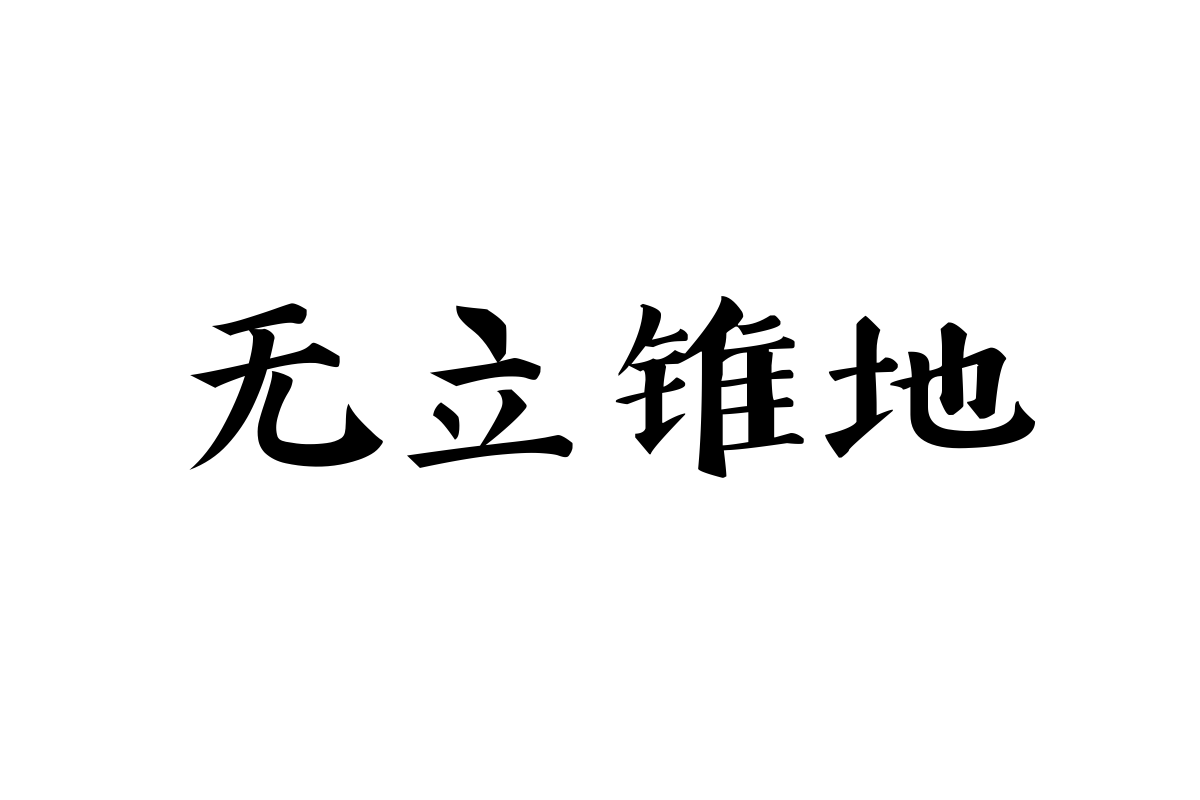
汉仪新蒂唐朝体是一套专为中文排版设计的字体,由汉仪字库公司推出。这套字体具有独特的风格和特点,旨在为设计师提供一种新颖、独特的字体选择。以下是对汉仪新蒂唐朝体的一些介绍:
1. 设计风格:汉仪新蒂唐朝体采用了唐朝时期的书法风格,笔画流畅、自然,具有很强的艺术感。这种设计风格使得字体看起来既有古典韵味,又不失现代感。
2. 字形结构:该字体的字形结构较为复杂,笔画较多,但整体布局紧凑,呈现出一种平衡和谐的感觉。这使得字体在视觉上具有较高的辨识度和美感。
3. 应用场景:汉仪新蒂唐朝体适用于各种与传统文化相关的设计项目,如书籍、杂志、海报、广告等。此外,由于其独特的风格,也适合用于创意设计、品牌标识等领域。
总之,汉仪新蒂唐朝体是一款独具特色的中文字体,它融合了传统与现代的元素,为设计师提供了丰富的字体选择。无论是在传统文化项目还是创意设计中,这款字体都展现出了强大的魅力和实用性。